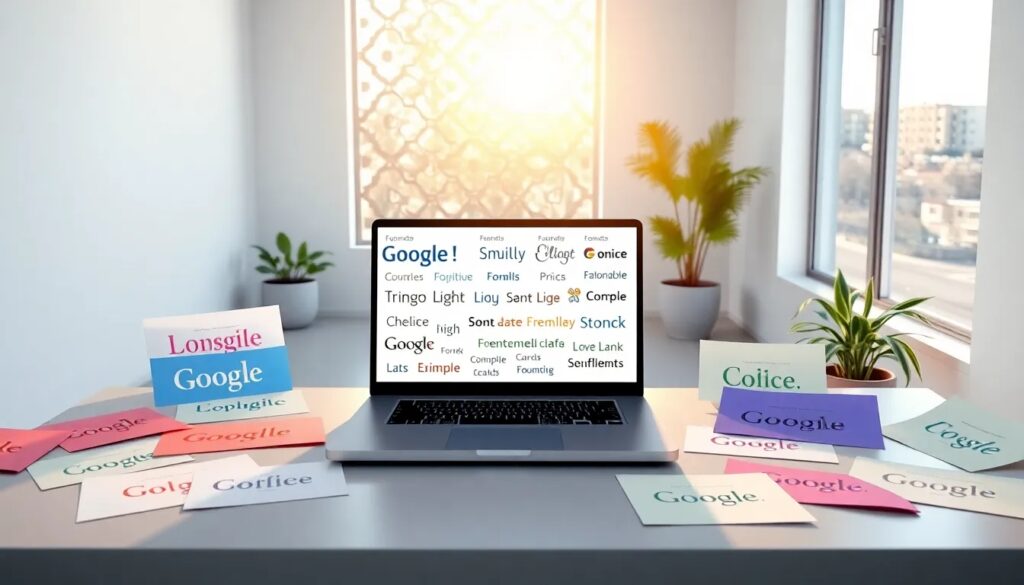
Google font: guía completa para su uso
Google Fonts se ha convertido en una herramienta fundamental para diseñadores y desarrolladores que buscan tipografías gratuitas y de alta calidad. Con su amplia biblioteca de fuentes, ofrece opciones versátiles que se adaptan a una variedad de proyectos creativos. En este artículo, exploraremos cómo utilizar Google Fonts efectivamente, sus ventajas, y las diferencias con otras bibliotecas de fuentes.
¿Para qué se pueden usar las fuentes de Google Fonts?
Las fuentes de Google Fonts son ideales para una amplia gama de aplicaciones. Desde sitios web hasta aplicaciones móviles, su uso es muy diverso. Aquí algunas de las formas más comunes de integrar estas fuentes:
- Diseño gráfico: se pueden utilizar en carteles, folletos y cualquier material impreso.
- Contenido web: perfectas para mejorar la legibilidad y la estética de un sitio.
- Aplicaciones móviles: integradas fácilmente a través de herramientas como Flutter.
- Contenidos audiovisuales: en presentaciones y videos, añadiendo un toque profesional.
La adaptabilidad de Google Fonts permite a los diseñadores personalizar proyectos y mantener una identidad visual coherente. Además, al ser fuentes de código abierto, no hay restricciones en su uso.
¿Qué diferencias existen entre Google Fonts y Adobe Fonts?
Aunque ambas bibliotecas ofrecen una amplia gama de fuentes, hay diferencias clave que pueden influir en tu elección:
- Selección: Cada plataforma tiene su propio estilo y calidad de fuentes, lo que puede ser crucial dependiendo del tipo de proyecto.
Considera estos aspectos al elegir la biblioteca de fuentes que mejor se adapte a tus necesidades.
¿Cuáles son las mejores fuentes de Google Fonts?
Algunas fuentes destacan por su popularidad y versatilidad. Aquí te presentamos una lista de las más recomendadas:
- Roboto: Ideal para interfaces de usuario, su diseño es moderno y legible.
- Open Sans: Perfecta para contenido en línea, gracias a su excelente legibilidad.
- Lato: Una fuente amigable que se adapta bien a cualquier proyecto.
- Montserrat: Excelente para títulos y encabezados, su estilo es contemporáneo.
- Playfair Display: Ideal para proyectos más elegantes, añade un toque clásico.
Cada una de estas fuentes tiene su propio estilo y puede ser utilizada en diferentes contextos, desde blogs hasta portafolios creativos.
¿Cómo utilizar Google Fonts en Flutter?
La integración de Google Fonts en aplicaciones móviles es un proceso sencillo gracias a Flutter. Para esto, sigue estos pasos:
1. Agrega el paquete de Google Fonts en tu archivo `pubspec.yaml`:
2. Importa el paquete en tu archivo Dart:
3. Utiliza la fuente en tu widget:
Esta facilidad de uso hace que Google Fonts sea una opción atractiva para desarrolladores que buscan personalizar el texto en sus aplicaciones.
¿Qué licencias ofrece Google Fonts para su uso?
Google Fonts utiliza licencias abiertas, lo que significa que puedes usar sus fuentes sin preocupaciones legales. Aquí algunos puntos clave sobre las licencias:
- Las fuentes son de uso gratuito en proyectos personales y comerciales.
- No se requiere atribución, aunque es apreciada en algunos casos.
- Las licencias son claras y están disponibles para revisión en el sitio web.
Esta transparencia y la posibilidad de utilizar las fuentes sin costo las convierten en una opción preferida para muchos.
- ¿Puedo usar Google Fonts en productos comerciales? Sí, son completamente gratuitas para uso comercial.
- ¿Google Fonts es compatible con aplicaciones móviles? Sí, se pueden integrar fácilmente en aplicaciones utilizando Flutter.
Estas respuestas pueden ayudarte a tomar decisiones informadas sobre el uso de Google Fonts en tus proyectos. Su versatilidad y facilidad de uso, junto con su amplia variedad de opciones, hacen de Google Fonts una herramienta imprescindible en el mundo del diseño.